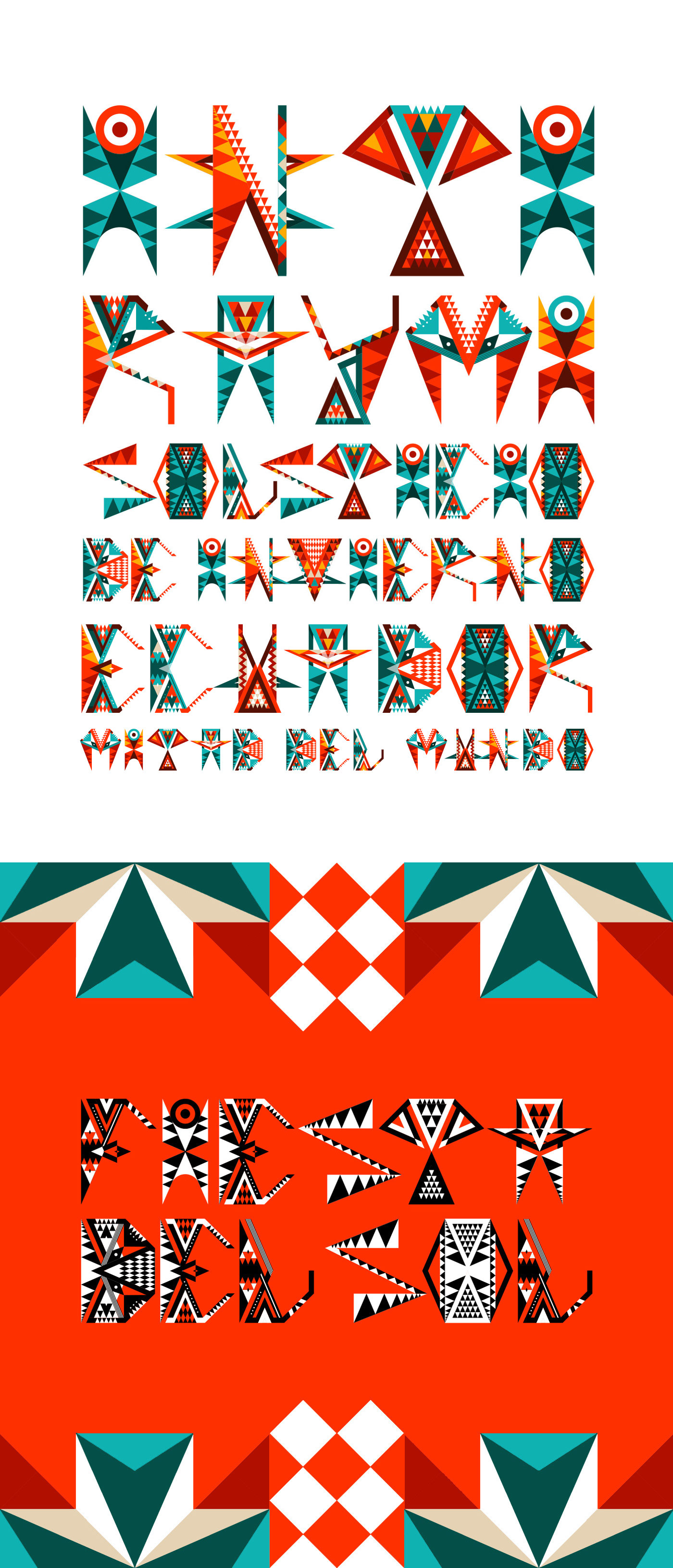
Color Font and Dingbat Inti
Tomando como punto de partida la matriz simbólica solar que el proyecto científico QUITSA TO desarrolla a partir del análisis del recorrido de la línea equinoccial que atraviesa el Monte “Catequilla”, un domo de 300 metros de altura que se encuentra ubicado en el medio de la cordillera oriental que servía para ver las salidas de los astros y la cordillera occidental que servía para observar las puestas de los mismos, convirtiéndose así en un observatorio perfecto para las observaciones astronómicas (Ecuador).